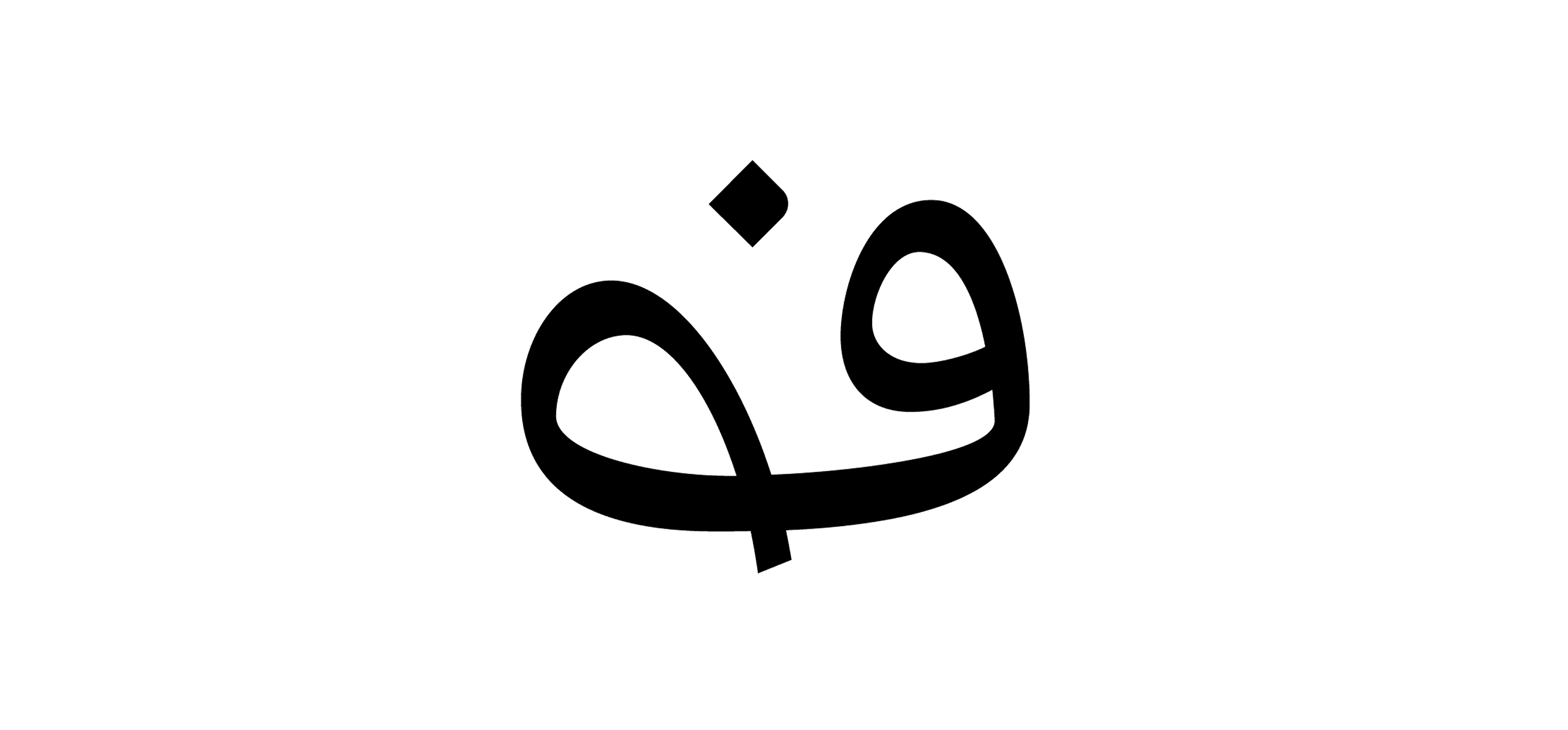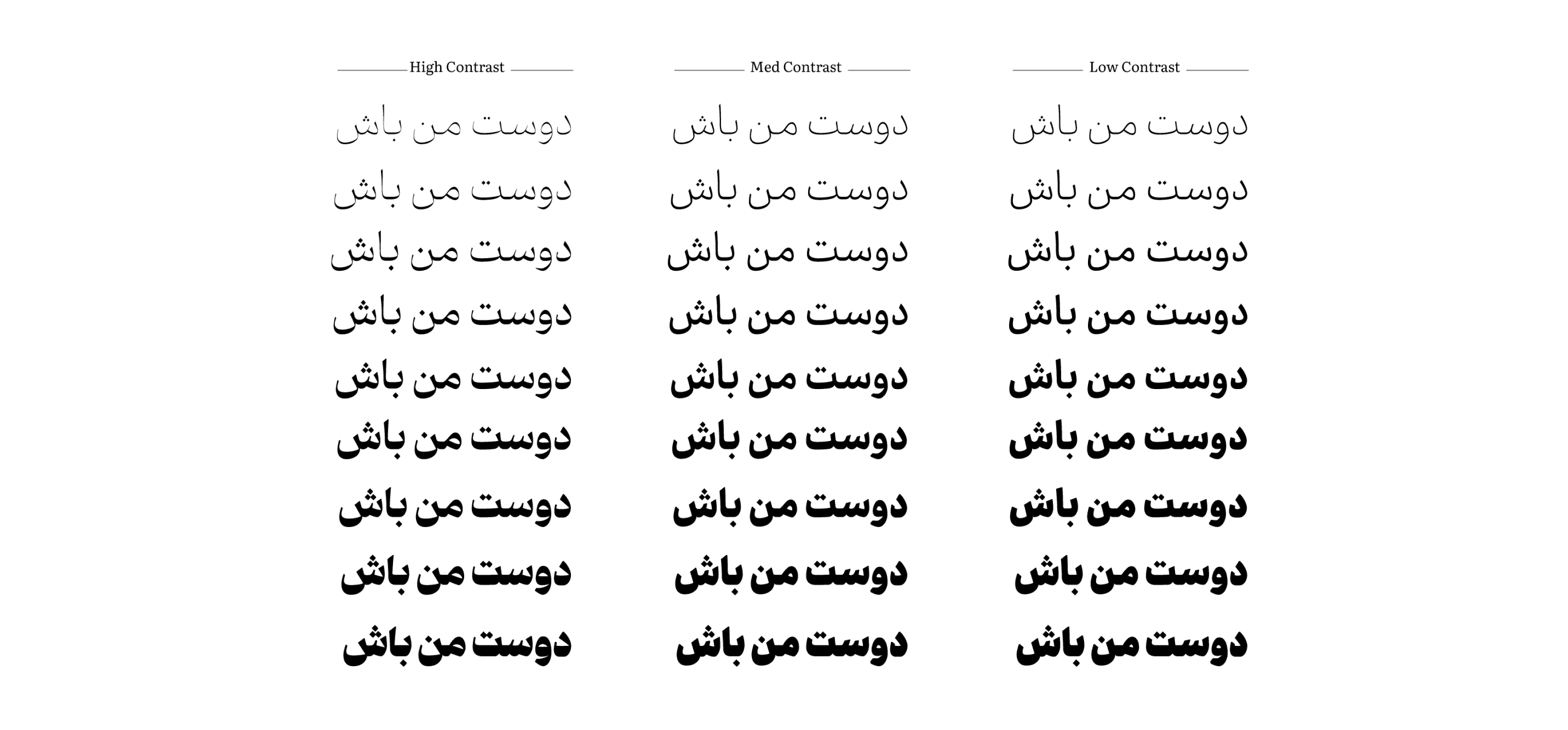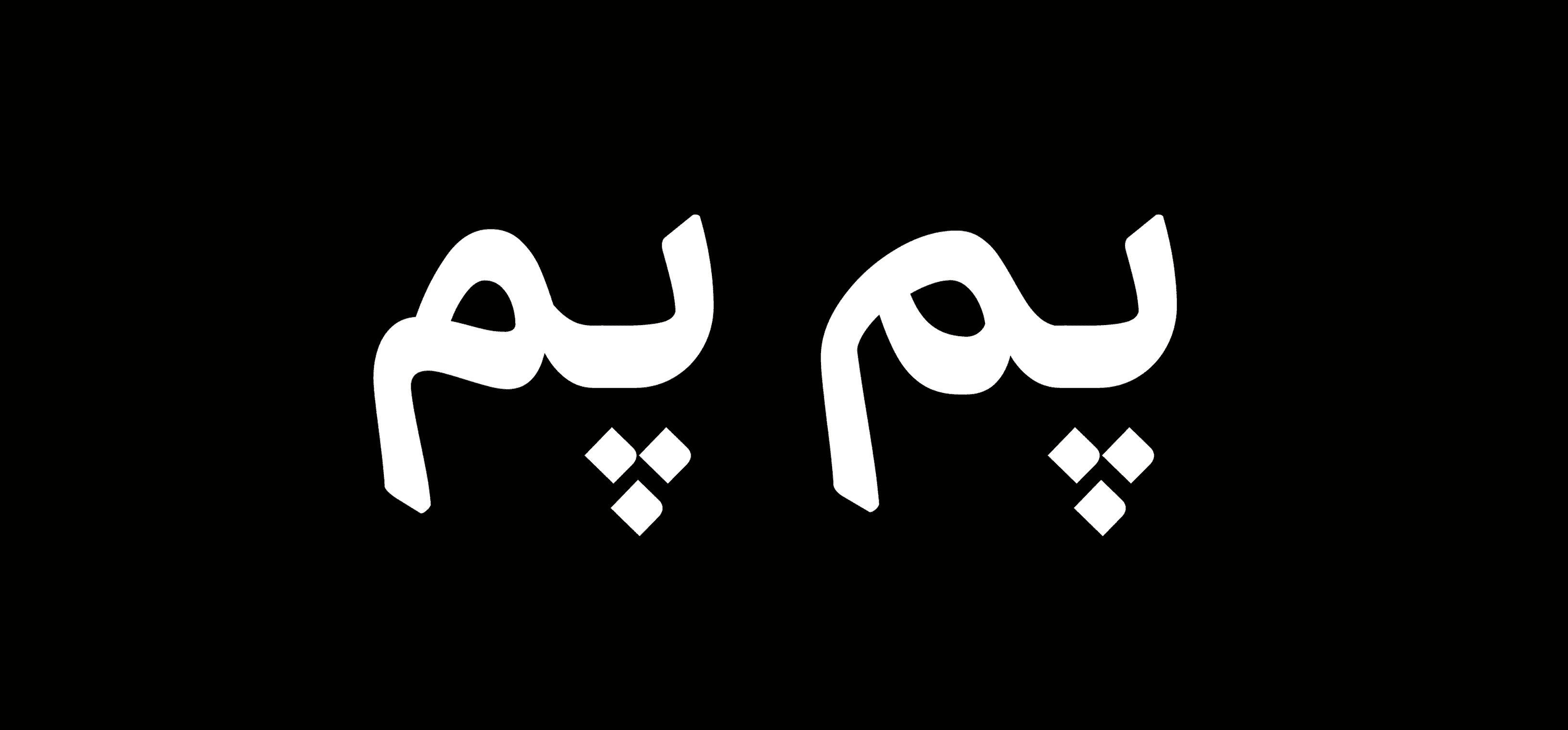
خط "ديباج" هو خط يروي الحكايات؛ يروي القصص، الأحداث، والمواقف الحياتية بلغة ودودة ودافئة.
تم تصميم هذا الخط منذ البداية ليُستخدم في النصوص الطويلة والسردية، لذا كان الحفاظ على الوضوح والقراءة السهلة، إلى جانب نبرة حميمة وسردية، من أبرز أولوياته.